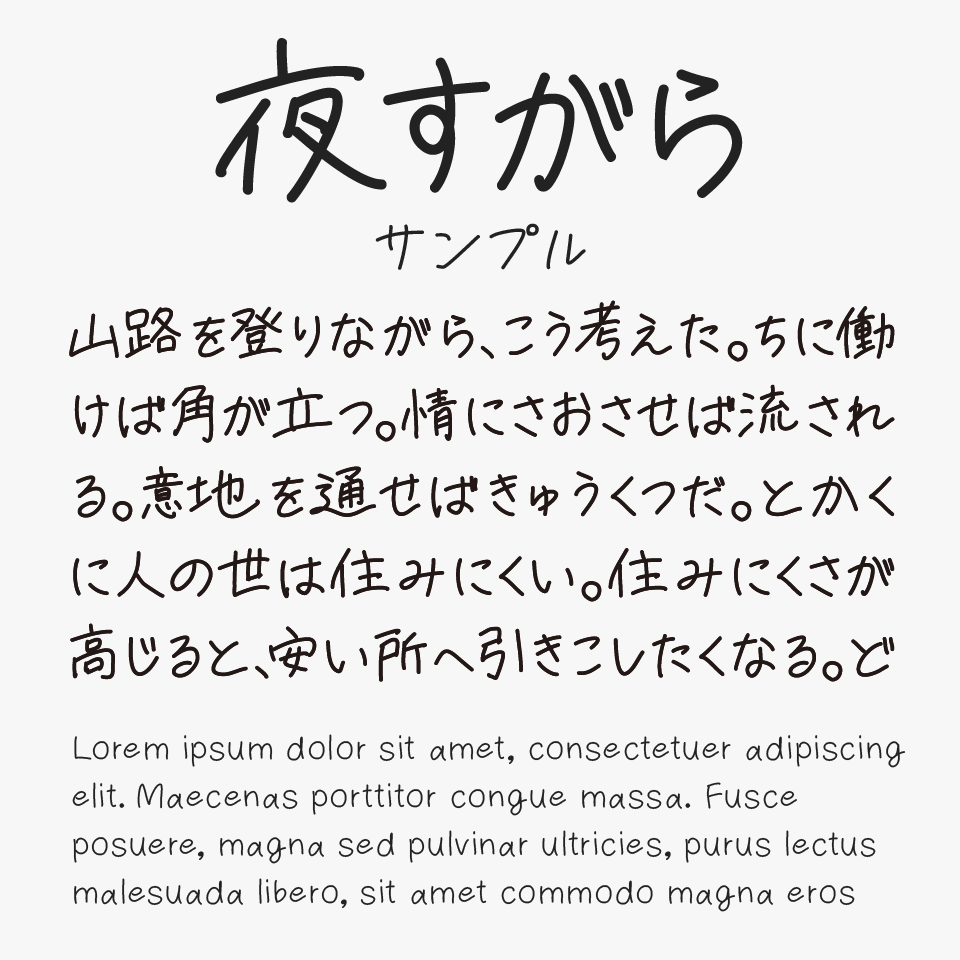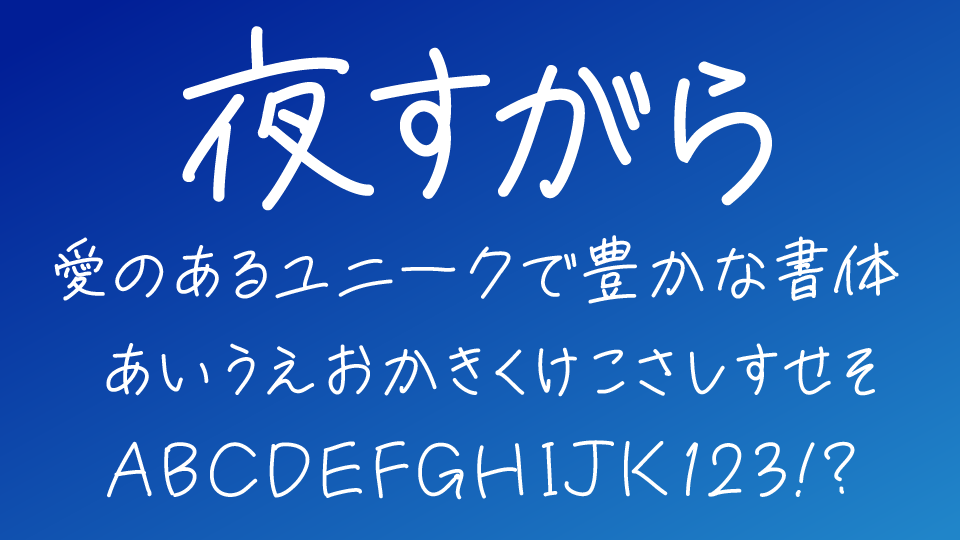
夜すがら手書きフォントは、作者が“夜な夜な書いたクセの強い文字”をもとに制作された、個性的な魅力あふれる手書きフォントです。
さらっと流れるような筆跡には、爽快感のある軽やかさがあり、一般的な可愛らしい手書きフォントとは少し違った、クールでかっこいい雰囲気を持っています。文字ごとに独特なクセや揺らぎがあり、その不均一さが絶妙なアクセントとなって、しっかりと手書きらしいリアルな表情を感じさせてくれます。
また、漢字は教育漢字(小学校6年生で習う範囲)まで収録されているため、短いフレーズだけでなく幅広いシーンで使いやすいところも魅力です。MV風デザインやSNS画像、ファッション系ビジュアル、サブカル系デザインなどにもぴったりで、“爽やかさ”と“クセのある個性”を両立した魅力的な手書きフォントとなっています。
個人的には、漢字が良い意味でクセがある字がとっても好きです。
夜すがら手書きフォントを、ほかのやわらかい雰囲気を持つ手書きフォントと比較してみると、爽やかさのある軽快な筆跡と、クセの強い個性的な表情が特に魅力です。
比較フォントは、「梅干フォント」「こよみゆる」「charifont」「ちはや純」「ぴろ字」と使用していますが、どれも“少しクセのある個性”なフォントなので、ぜひあわせてチェックしてみてください。
収録文字は、ひらがな・カタカナ・漢字は教育漢字(小学校6年生で習うものまで)まで収録されています。